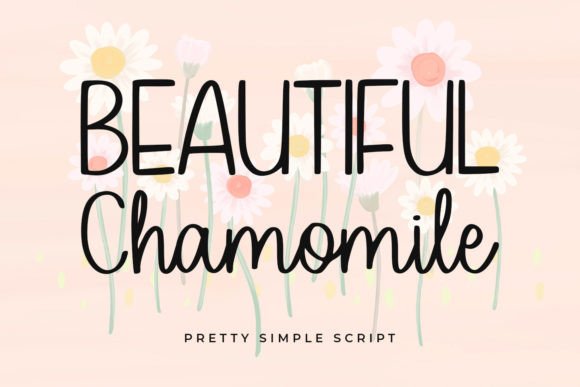
Beautiful Chamomile
Qu'est-ce que Beautiful Chamomile ?
Beautiful Chamomile est une police d'écriture script simple et élégante qui sait séduire. Conçue pour donner vie à vos créations, elle est un choix idéal pour créer des identités visuelles, des citations, des logos, des conceptions de t-shirt, de sacs à dos, de cartes, de bannières, de réseaux sociaux et bien plus encore.
Présentation de l'Écriture
Beautiful Chamomile est une police d'écriture qui brille par sa simplicité et son charme. Elle est conçue pour être facile à lire et à comprendre, ce qui la rend idéale pour les projets visuels qui nécessitent une touche de personnalité.
Utilisations de la Police d'Écriture
- Identités visuelles (logos, cartes de visite, etc.)
- Citations et textes inspirants
- Conceptions de t-shirt et de sacs à dos
- Cartes et bannières
- Réseaux sociaux et contenus numériques
- Plus encore...
Conclusion
Beautiful Chamomile est une police d'écriture qui sait séduire et captiver. Avec sa simplicité et son charme, elle est un choix idéal pour les créateurs qui cherchent à donner vie à leurs projets visuels. Alors, découvrez la beauté de Beautiful Chamomile et donnez vie à vos créations !